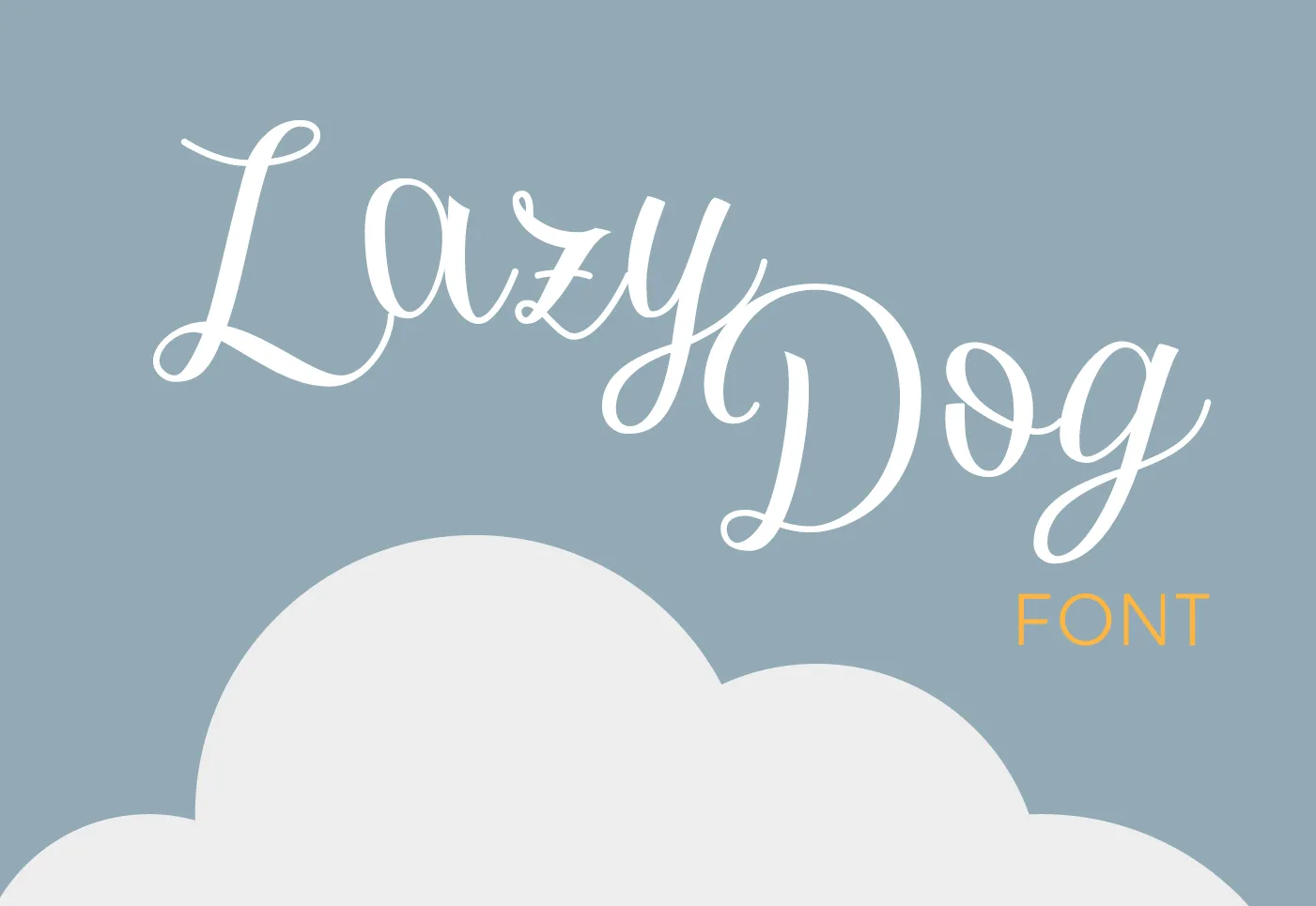
Lazy Dog Font – Fonte Grátis
Lazy Dog Font
A Lazy Dog Font é uma elegante seleção do tipo Brush Handwriting Display Typefaces que combina graça com força. Ideal para ambientes criativos onde o estilo e a facilidade na utilização são fundamentais, ela oferece um conjunto variado de ligações diferentes, acessíveis através do teclado usando a função Opentype. Esta fonte foi projetada especificamente para o alfabeto latino e vem equipada com uma completa gama de accents e diacritics. Ideal para designers que buscam simplificar seu processo criativo sem sacrificar qualidade, Lazy Dog é perfeitamente adaptado aos ambientes digitais onde a rapidez pode ser tão importante quanto a beleza visual. Com sua facilidade de uso e estilo distintivo, é uma escolha ideal para qualquer projeto que valorize tanto o cuidado no design quanto o conforto na criação. Monofonts criou esta fonte com uma visão clara: facilitar o trabalho dos designers sem sacrificar a qualidade ou a personalidade do tipo de letra.
Designer: Monofonts